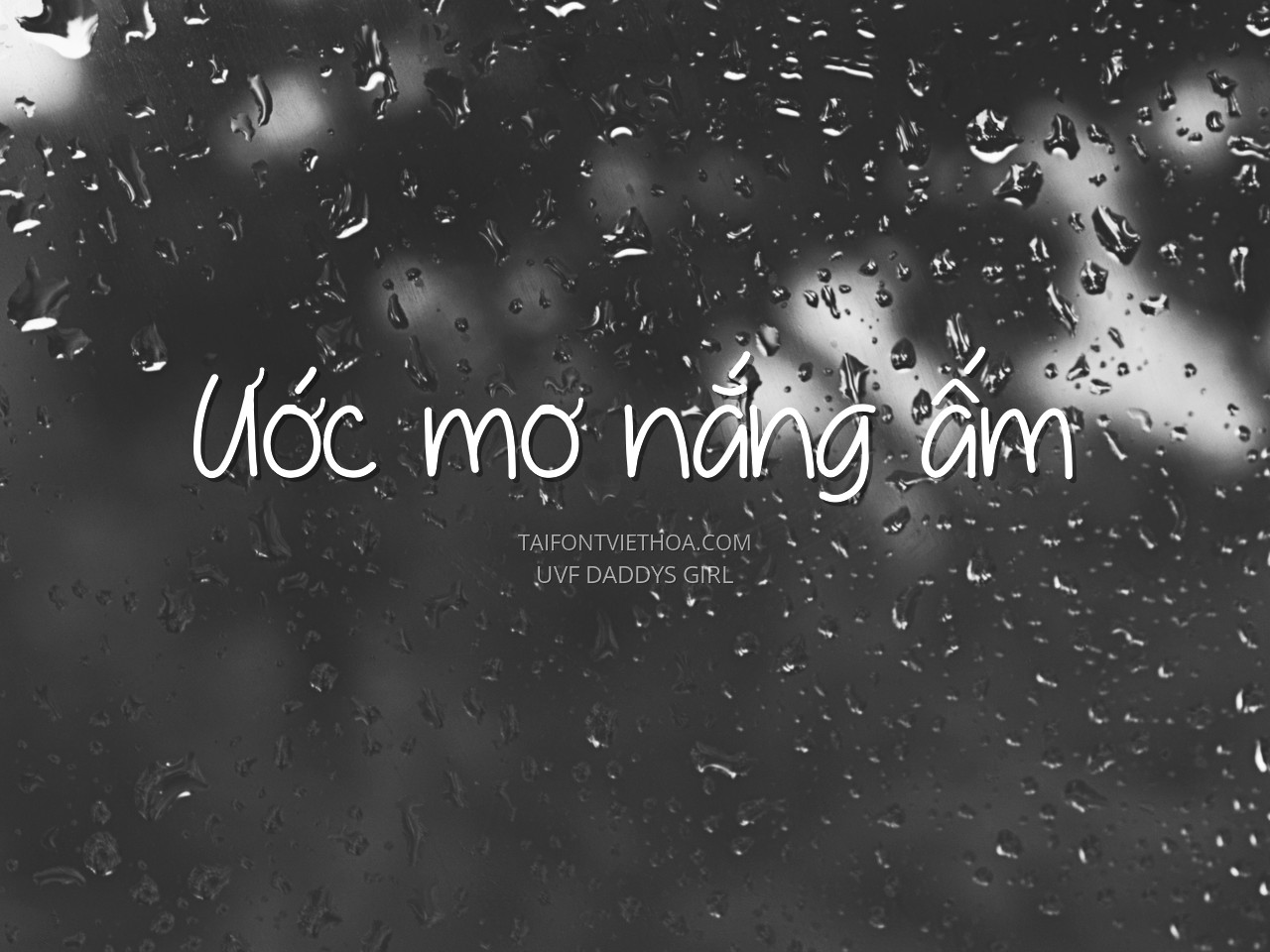
Font việt hóa UVF Daddysgirl
Giới thiệu về font UVF Daddysgirl
UVF Daddysgirl là một font chữ dễ thương mang đậm cảm hứng thiếu nhi và tình cảm gia đình, đặc biệt gợi liên tưởng đến sự gắn bó giữa cha và con gái. Với phong cách viết tay nhẹ nhàng, ngộ nghĩnh và gần gũi, font rất phù hợp cho các thiết kế dành cho trẻ em, sản phẩm giáo dục, hoặc các nội dung hướng đến cảm xúc và sự đáng yêu. Font đã được sưu tầm và chia sẻ bởi thành viên Font Chuẩn và hiện được taifontviethoa.com sử dụng trong các dự án liên quan đến đồ chơi, sản phẩm học tập, hoặc truyền thông giáo dục sáng tạo.
Đặc điểm thiết kế và ứng dụng của UVF Daddysgirl
UVF Daddysgirl mang phong cách hand-drawn với đường nét đơn giản, tròn trịa và mềm mại. Các ký tự được cách điệu theo phong cách vui tươi, không quá đều đặn, tạo sự ngẫu hứng và sinh động như một nét vẽ của trẻ thơ. Font hỗ trợ đầy đủ tiếng Việt, mang đến trải nghiệm sử dụng linh hoạt trong thiết kế số và in ấn.
Ứng dụng lý tưởng: thiết kế sách truyện thiếu nhi, poster lớp học, bao bì đồ chơi, bảng hiệu tiệm quà lưu niệm hoặc các sản phẩm mang thông điệp tích cực, yêu thương. Ngành nghề phù hợp: giáo dục mầm non, giải trí trẻ em, quà tặng, đồ handmade, tổ chức sự kiện hoặc thương hiệu dành cho mẹ và bé.